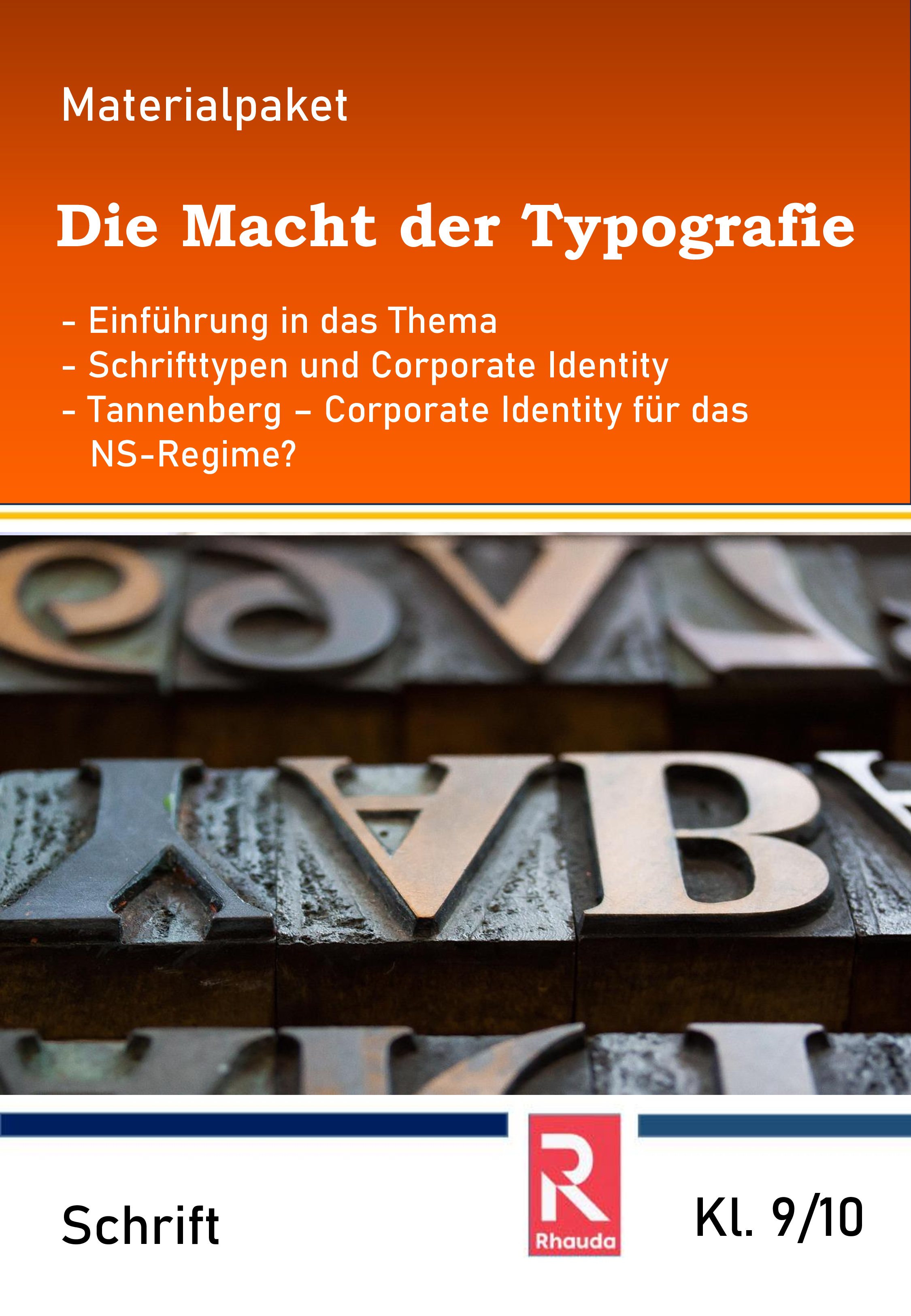
Dieses Materialpaket betrachtet weniger die technischen Feinheiten und Fachterminologie von Schrift, sondern beleuchtet deren Wirkung und Anwendungsbereiche. Schüler/innen reflektieren ihre Wahrnehmung von Schrift, lernen verschiedene Schriftarten und deren Wirkung und Einsatz kennen und wenden verschiedene Schriftarten reflektiert an.
Im Fachübergriff mit Geschichte betrachten die Schüler/innen die Wirkung von gebrochenen Schriften, lernen am Beispiel der Schrift "Tannenberg" deren Anwendung während der NS-Zeit kennen und diskutieren anschließend, ob Schriften neutral sein können.